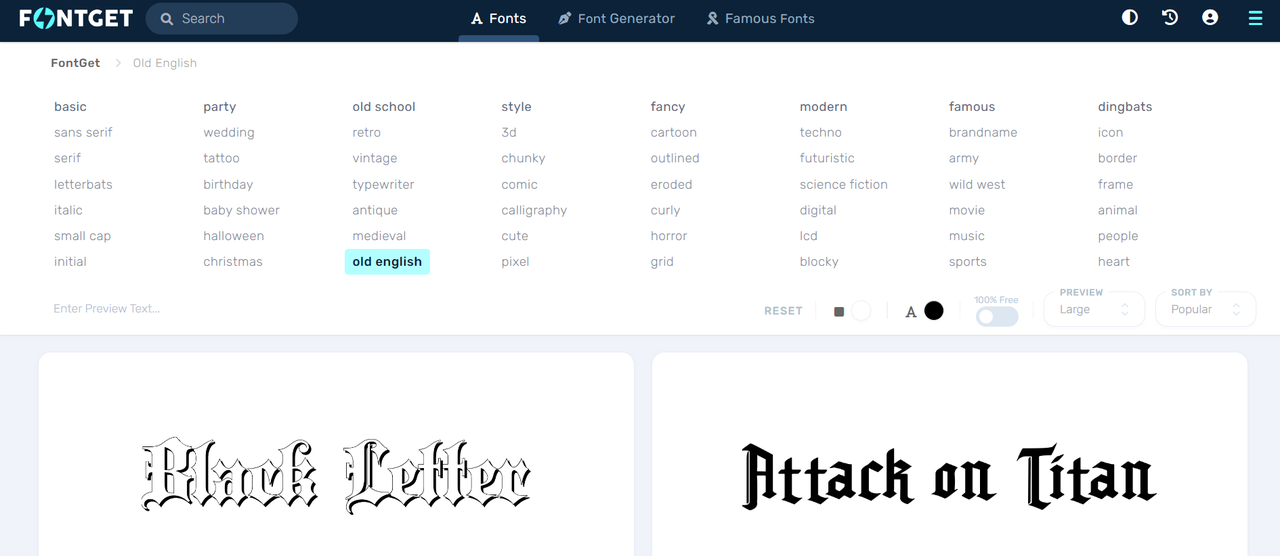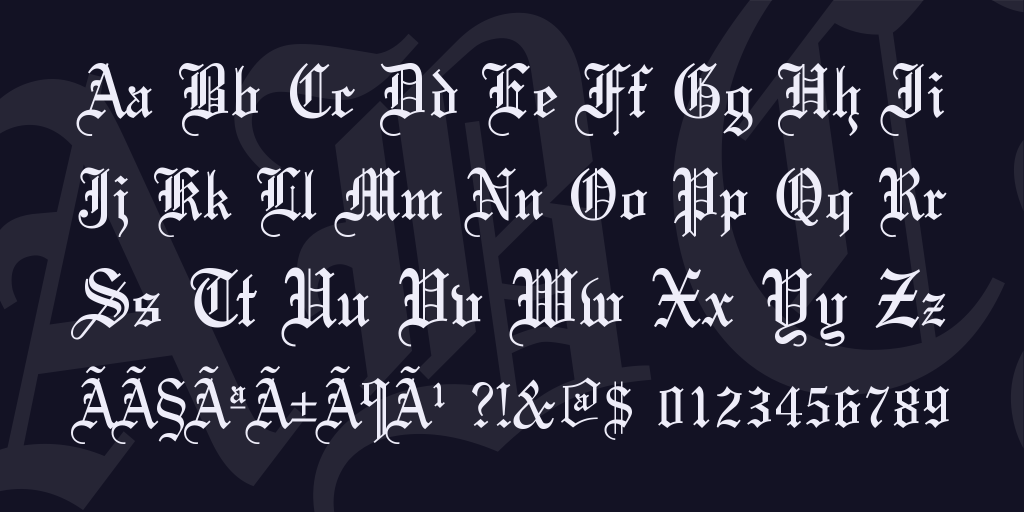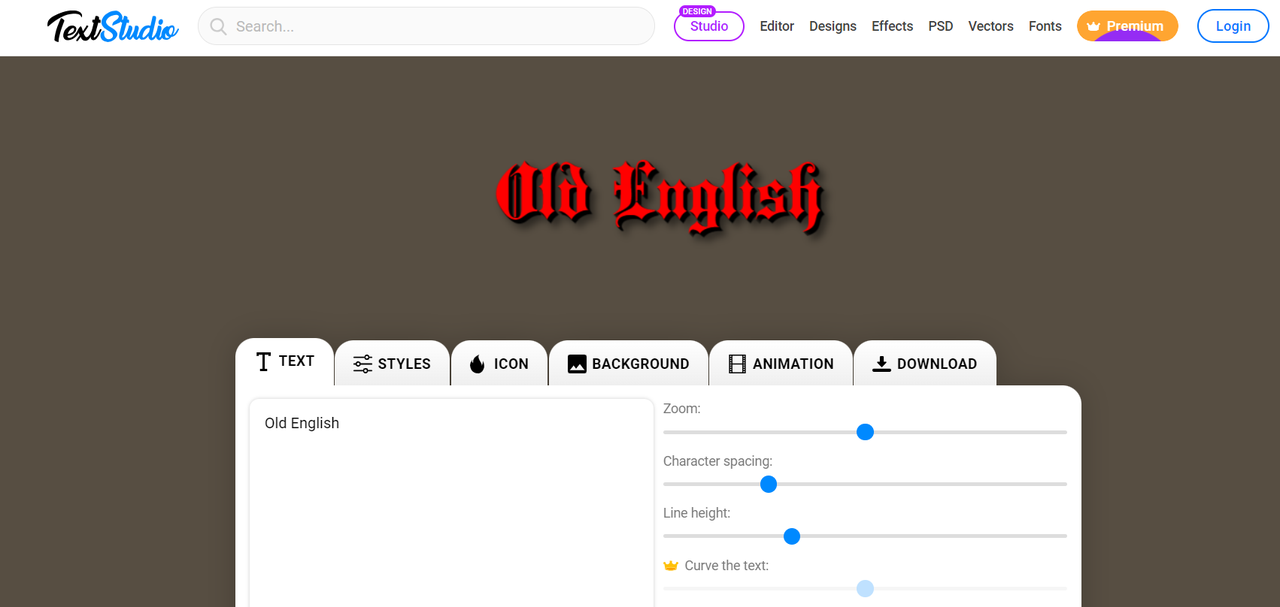
I migliori 5 generatori di caratteri inglesi antichi per disegni di testo vintage
Stai cercando di aggiungere un tocco di eleganza e tradizione ai tuoi progetti? Un vecchio generatore di font inglese può far risaltare i tuoi inviti di nozze, poster di eventi e design di prodotti. Scopri come questi strumenti possono trasformare i tuoi progetti e dare loro un aspetto classico e senza tempo. Immergiti e scopri la magia!
Perché i vecchi generatori di font inglesi sono strumenti essenziali per i designer
Quando si cerca di impregnare i design con un tocco di eleganza senza tempo e fascino storico, i vecchi generatori di caratteri inglesi si rivelano indispensabili. Ecco perché i designer ne hanno bisogno:
• Accessibilità: Forniscono un facile accesso ai caratteri in inglese antico senza la necessità di conoscenze specialistiche di calligrafia o tipografia.
• Alta efficienza: Invece di creare manualmente i caratteri, i generatori offrono accesso immediato a una vasta gamma di stili di inglese antico, risparmiando tempo nei progetti di design.
• Personalizzazione: Molti generatori consentono ai designer di personalizzare aspetti come dimensioni, variazioni di stile e talvolta anche spaziatura delle lettere, adattando i caratteri alle specifiche esigenze del progetto.
• Ispirazione: generatori di caratteri in inglese antico stimolano la creatività offrendo forme di lettere uniche e ornate. Può facilitare disegni con un'estetica storica o sofisticata.
5 migliori vecchi generatori di caratteri inglesi
1. Meme del carattere
Font Meme offre un'ampia selezione di vecchi caratteri inglesi perfetti per qualsiasi progetto di design. Fornisce un'interfaccia facile da usare per visualizzare in anteprima e generare testo. Font Meme è l'ideale per i designer che cercano opzioni tipografiche classiche ed eleganti.
Caratteristiche principali:
• Ampia selezione di vecchi caratteri inglesi
• Generatore di testo facile da usare
• Funzione di anteprima per vedere i caratteri in azione
2. FontSpace
FontSpace è una risorsa di font popolare che offre una varietà di vecchi font inglesi. Permette ai designer di scaricare e utilizzare questi font per progetti personali e commerciali. FontSpace è noto per la sua vasta collezione e la facile accessibilità.
Caratteristiche principali:
• Vasta collezione di vecchi caratteri inglesi
3. FontGet
FontGet fornisce una vasta gamma di vecchi caratteri inglesi per varie esigenze di progettazione. Offre un processo di download semplice e una varietà di stili tra cui scegliere. FontGet è una fonte go-to per i progettisti che cercano caratteri di alta qualità.
Caratteristiche principali:
• Vasta gamma di vecchi caratteri inglesi
• Personalizza il colore del carattere, il colore dello sfondo e la dimensione del carattere
• Vari stili disponibili
4. Piliapp
Piliapp dispone di un generatore di testo online per vecchi caratteri inglesi, che semplifica la creazione di testo elegante. Fornisce una piattaforma user-friendly con opzioni di personalizzazione rapida. Piliapp è perfetto per coloro che hanno bisogno di generare rapidamente vecchi testi inglesi.
Caratteristiche principali:
• Modelli di testo ed effetti unici
• Opzioni di personalizzazione rapida
• Anteprima in tempo reale
Quando si sceglie un vecchio creatore di testo inglese, dare la priorità a fattori come la varietà dei caratteri, la facilità d'uso, le opzioni di personalizzazione e la qualità dell'output. Per integrare perfettamente i vecchi caratteri inglesi nei progetti video, CapCut eccelle con la sua vasta libreria di caratteri, strumenti di editing intuitivi e capacità di output ad alta risoluzione. Non è solo un creatore di testo, ma un potente strumento di editing video che migliora la narrazione con accattivante vecchia tipografia inglese.